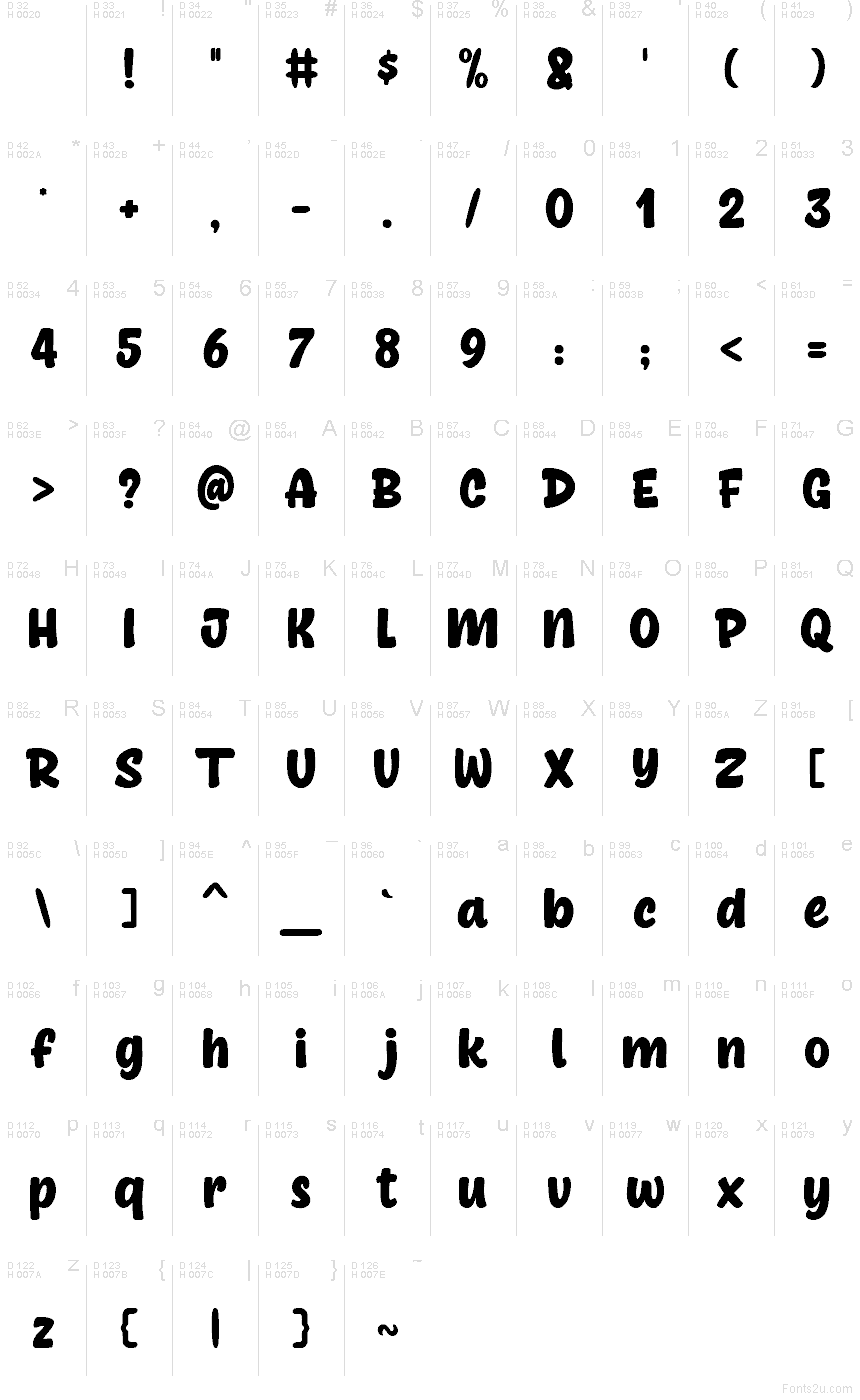
La Petite Chanteuse par BlackFridayFont est une police de caractères d'affichage de type dessin animé gratuite avec des lettrages épais et dessinés à la main. Des courbes douces, des largeurs de trait irrégulières et des formes de lettres espiègles confèrent au design le dynamisme d'une enseigne de magasin peinte.
L'emballage constitue un terrain idéal pour ses formes enjouées, en particulier sur les confiseries, les jouets et les marques alimentaires décontractées. Elle convient également à l'édition jeunesse et aux affiches d'événements. Les formes sympathiques s'adressent directement à un public jeune et aux entreprises familiales à la recherche de lettrages illustrés.